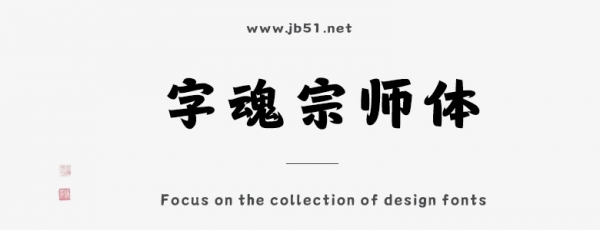
字魂宗師體是由字魂字庫商用的楷體,創(chuàng)意字,這款字體包含7144個中文、字母、 符號和數(shù)字,具有中國風(fēng)的風(fēng)格,適合應(yīng)用于藝術(shù)設(shè)計、平面宣傳設(shè)計、網(wǎng)頁設(shè)計,書法字帖等領(lǐng)域。
字魂宗師體字體是一款商用的楷體,創(chuàng)意字體,該字體包含7144個中文、字母、 符號和數(shù)字,具有中國風(fēng)的風(fēng)格,可以滿足您設(shè)計上的各種需求,該字體主要用于黨政公務(wù)等場景, 您不但可以在字魂網(wǎng)下載字魂宗師體字體,同時還有眾多毛筆書法字體、創(chuàng)意字體等可供選擇!